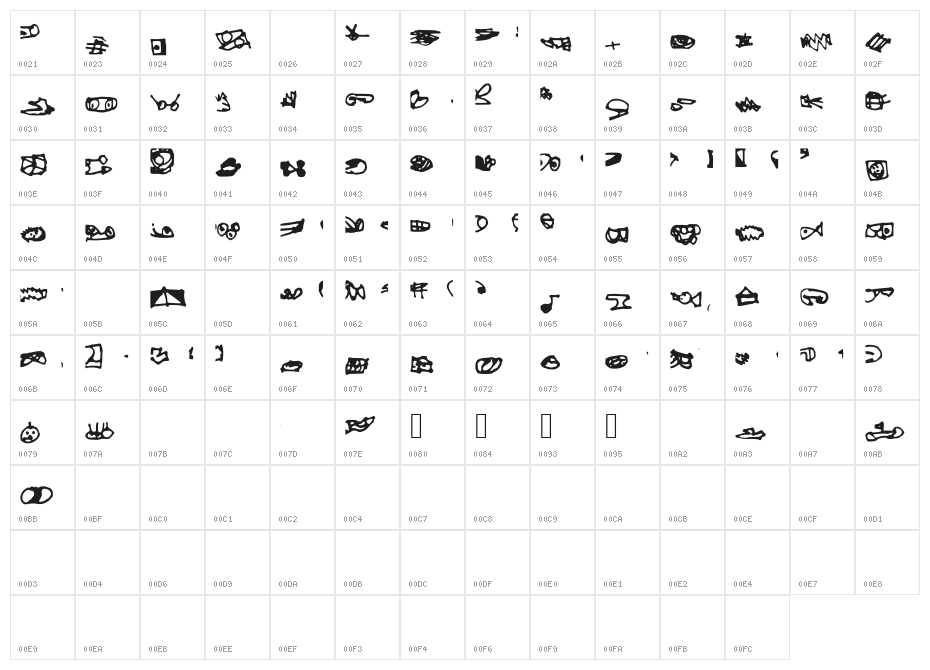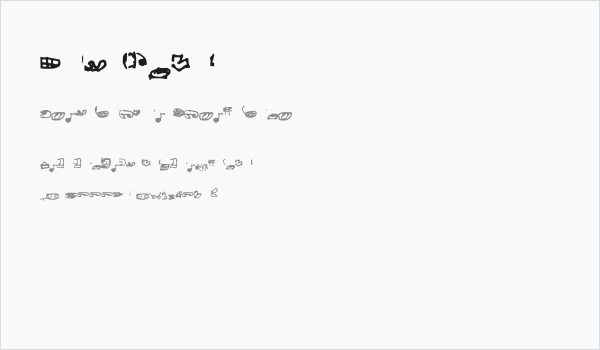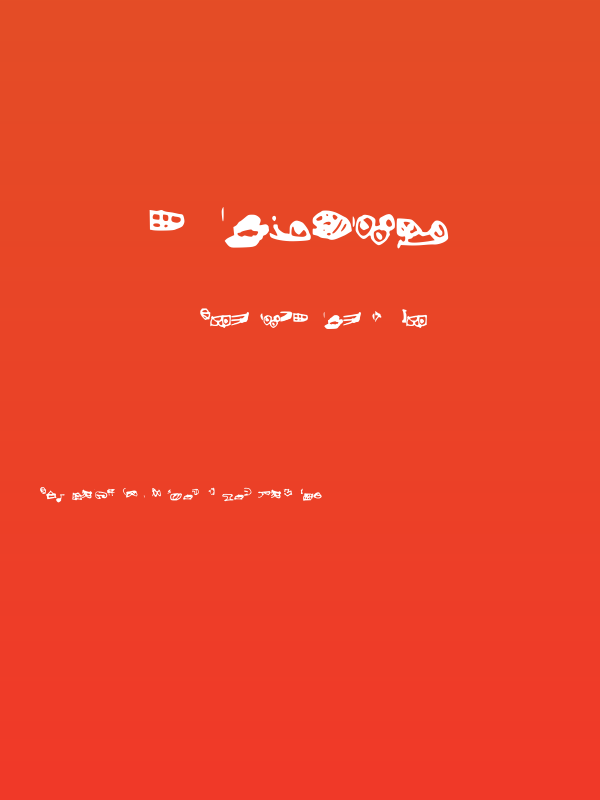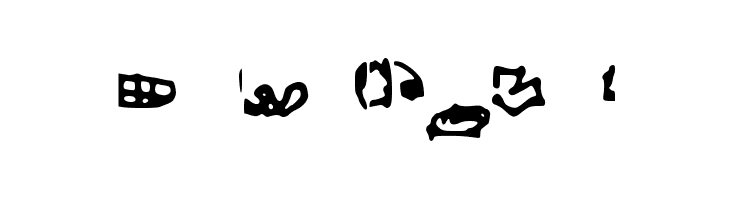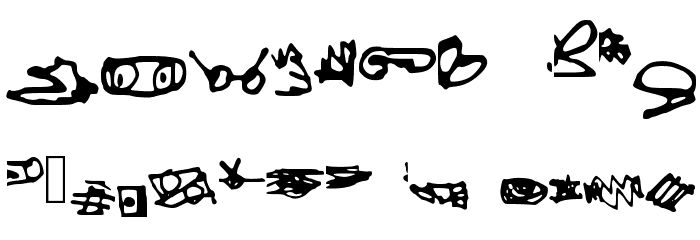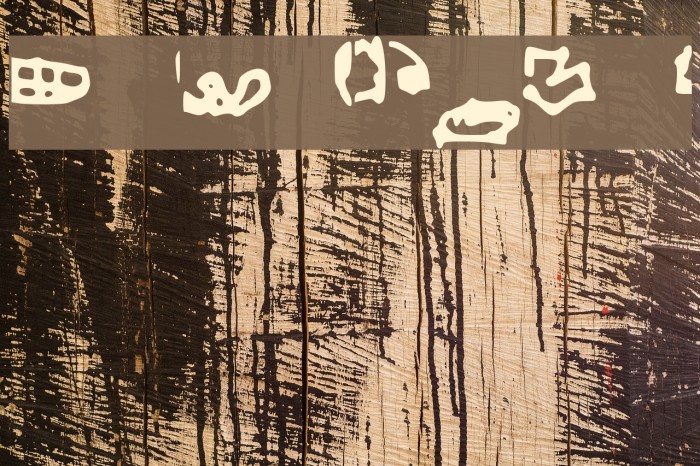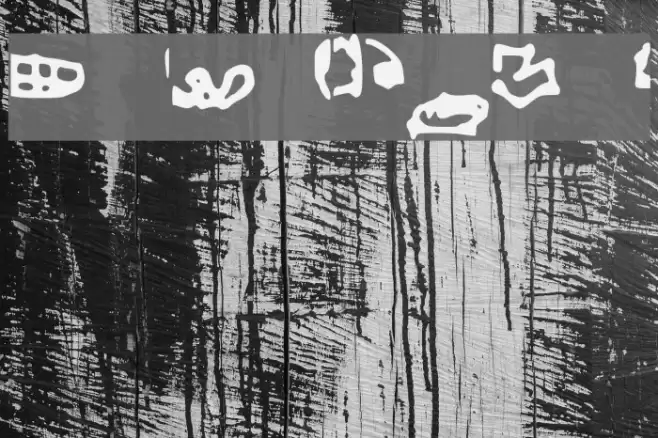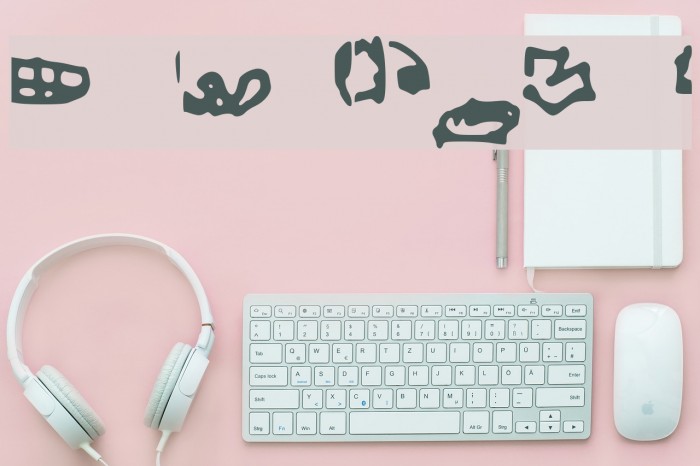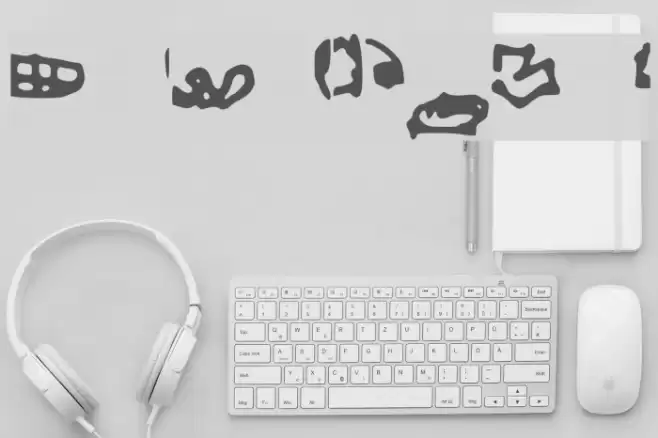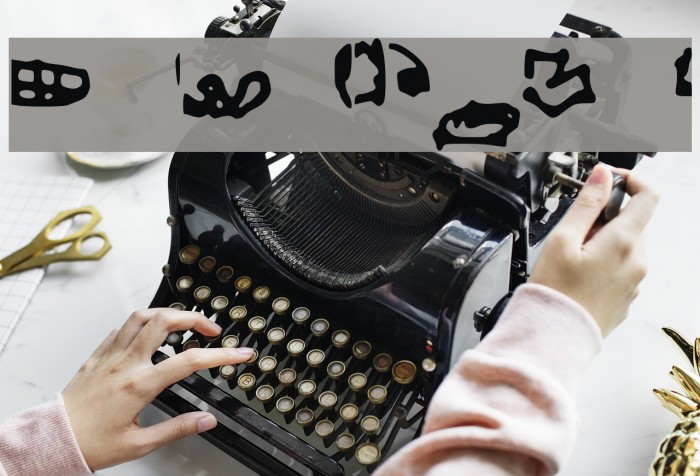
✎ Dingbats
このフォントには 143 文字が含まれています。文字をクリックして詳細を表示。
| 全体的なスタイル | Abstract, Experimental, Decorative |
| 用途 | Art installations, experimental posters, cryptic branding |
| おすすめプロジェクト | Experimental art, cryptic designs, avant-garde posters, or projects needing an unreadable, mysterious look. |